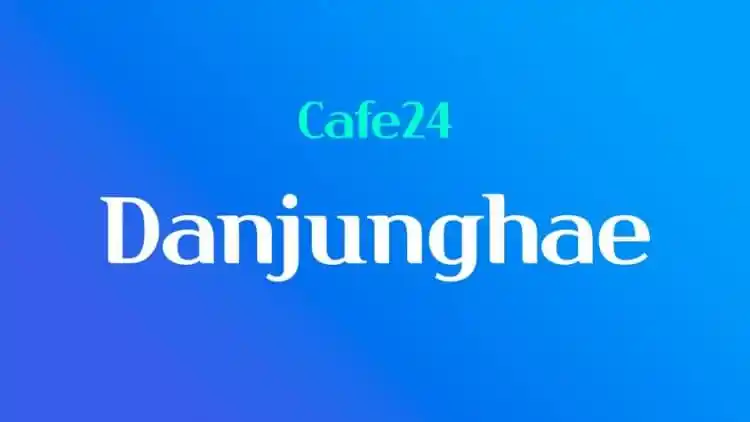
A Danjunghae Sans Serif é uma tipografia sans serif e humanista com um design limpo. Inspirada na beleza e elegância de estilos modernos de tipografia, ela se destaca como uma opção perfeita para uma ampla gama de usos visuais. Confortável tanto em uso individual quanto em aplicações publicitárias, a Danjunghae é ideal para logotipos, outdoors, headlines e citações. Suas linhas retas e elegantes garantem um estilo minimalista ao mesmo tempo que mantêm uma personalidade de tipografia moderna. Não perca essa oportunidade de adicionar beleza e sofisticação a qualquer projeto visual com a Danjunghae Sans Serif Font.